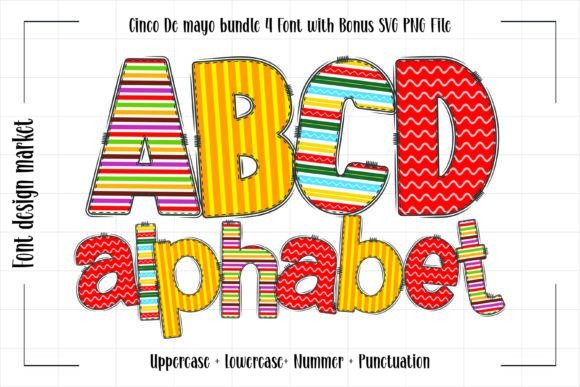
Cinco De Mayo Font
Cinco De Mayo Font – أضف لمسة احتفالية إلى تصاميمك!
استمتع بجو الاحتفالات مع Cinco De Mayo Font، الخط المثالي لإضفاء طابع مكسيكي أصيل ومبهج على تصاميمك! يتميز هذا الخط بتصميمه الفريد الذي يجمع بين المرح والأناقة، مما يجعله الخيار الأمثل للمشاريع الإبداعية مثل:
✅ التصاميم الدعائية والملصقات
✅ الشعارات والعلامات التجارية
✅ دعوات الحفلات والمهرجانات
✅ تصميم القمصان والمنتجات المطبوعة
✅ منشورات وسائل التواصل الاجتماعي
Cinco De Mayo Font يمنحك تجربة تصميم ممتعة مع خطوط انسيابية وحواف مستوحاة من الفن المكسيكي التقليدي. أضف لمسة نابضة بالحياة واجعل إبداعك يتألق مع هذا الخط الفريد!